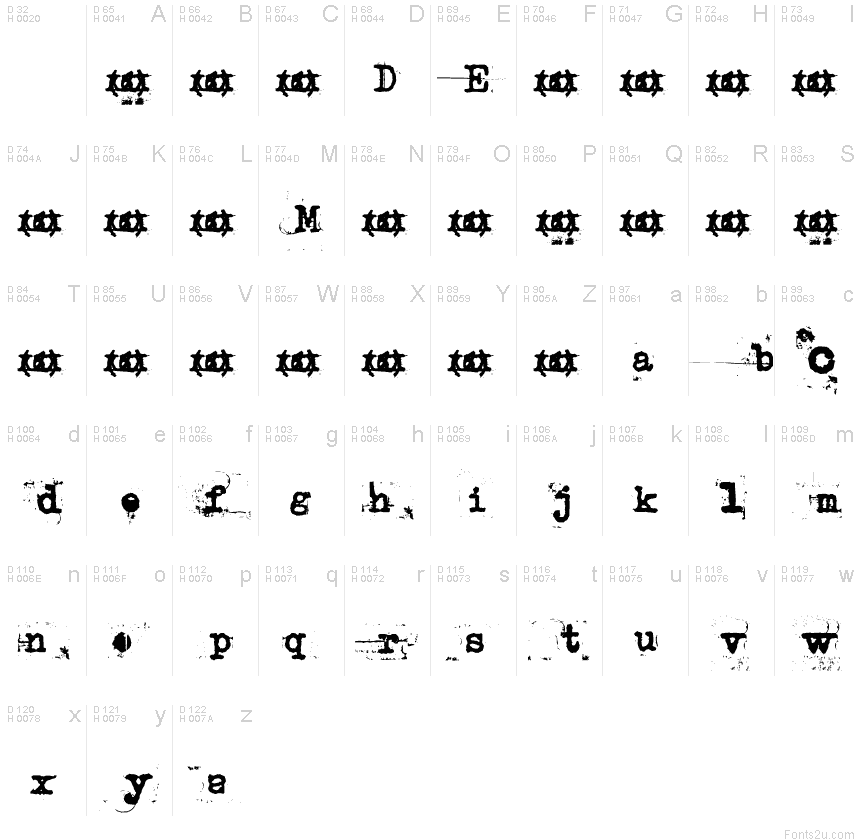
Uncletypewriter, zaprojektowany przez Germana Olayę, to darmowy, wyrazisty krój pisma typu display stylizowany na maszynę do pisania. Charakteryzuje się ciężkimi, rozmytymi literami o nierównych, poszarpanych krawędziach. Wygląda jakby tekst był odbity mocno zużytą taśmą barwiącą, a surowa, grunge'owa faktura sprawia, że znaki wyglądają na wytarte i autentyczne.
Świetnie sprawdzi się na plakatach, w zinach, na okładkach płyt, książek czy w napisach filmowych wszędzie tam, gdzie typografia ma być „namacalna”, a nie wygładzona. Jako darmowy font idealnie nadaje się do krótkich nagłówków i cytatów, ponieważ masywne formy i drapana tekstura nadają nawet kilku słowom ten niepokojący klimat zniszczonego dokumentu.